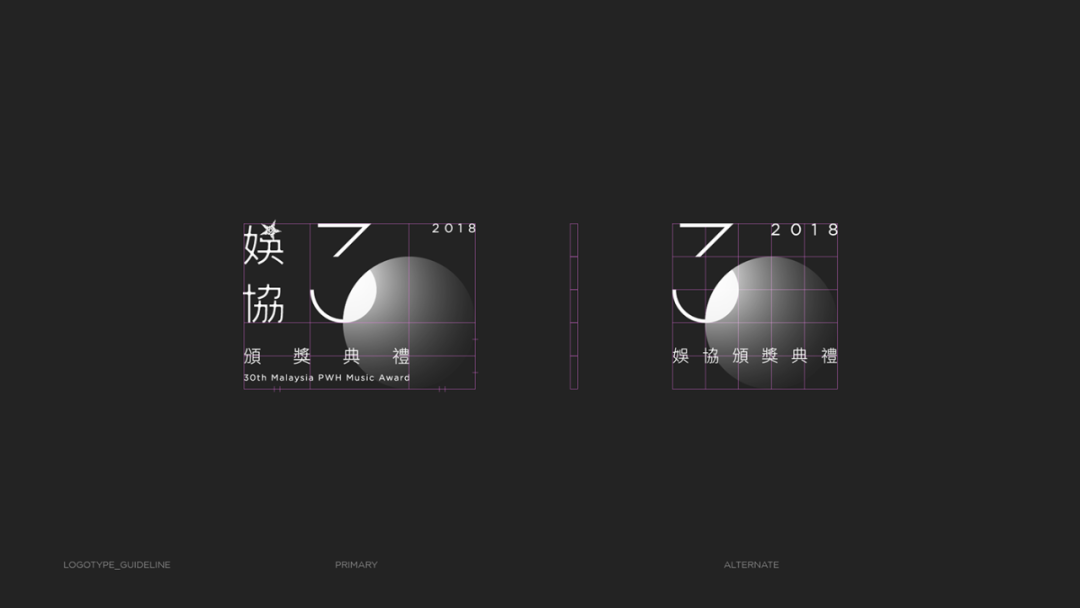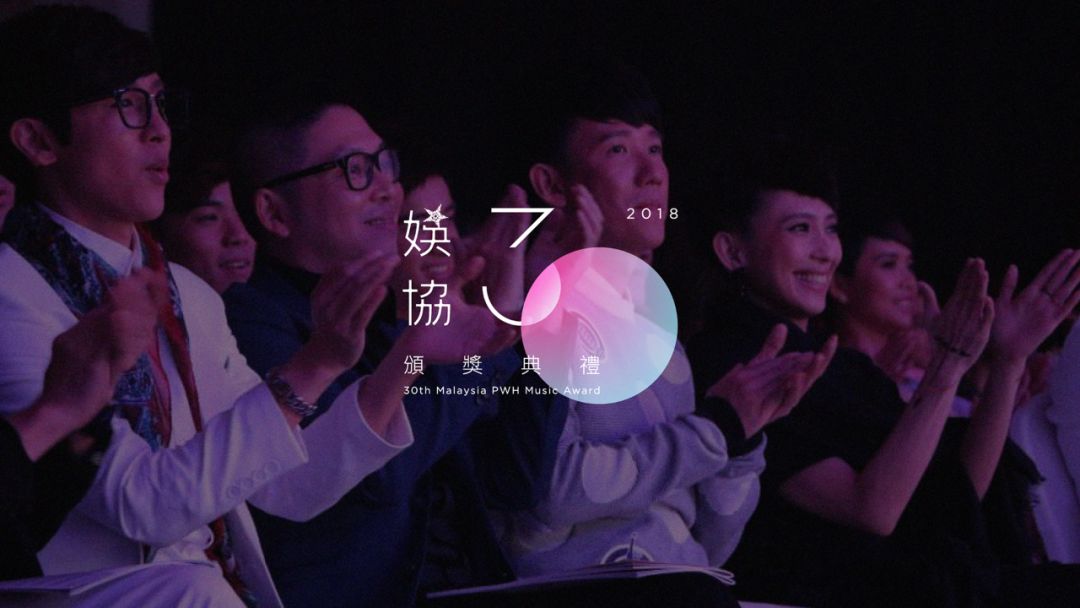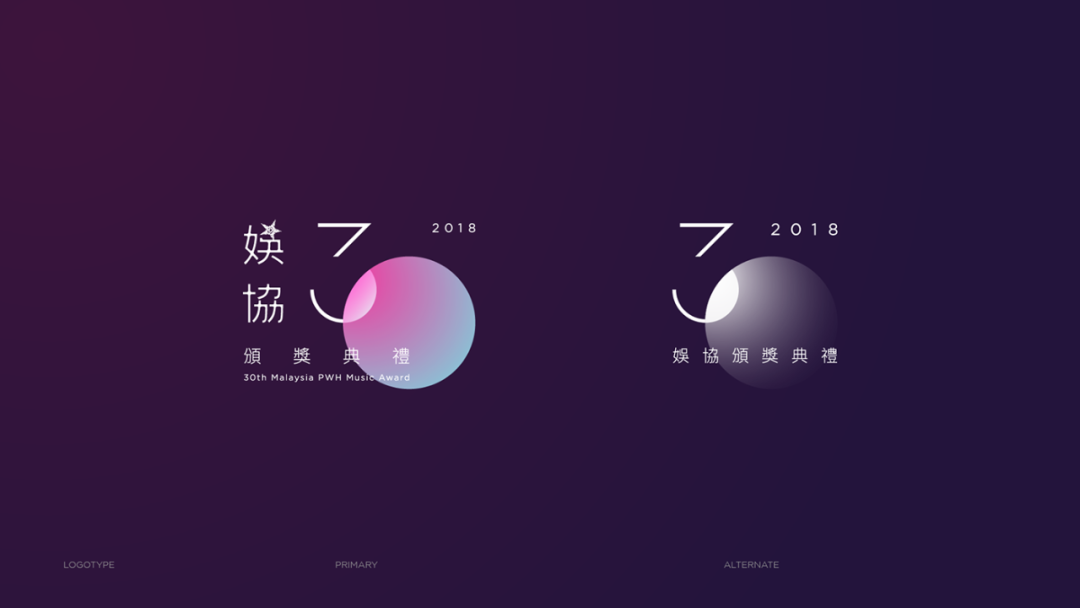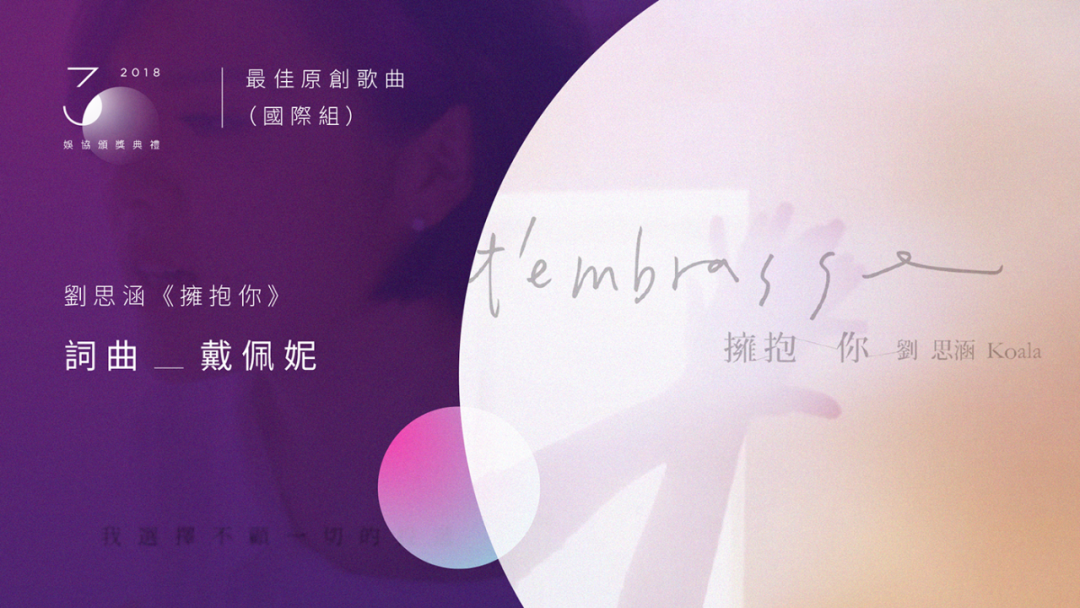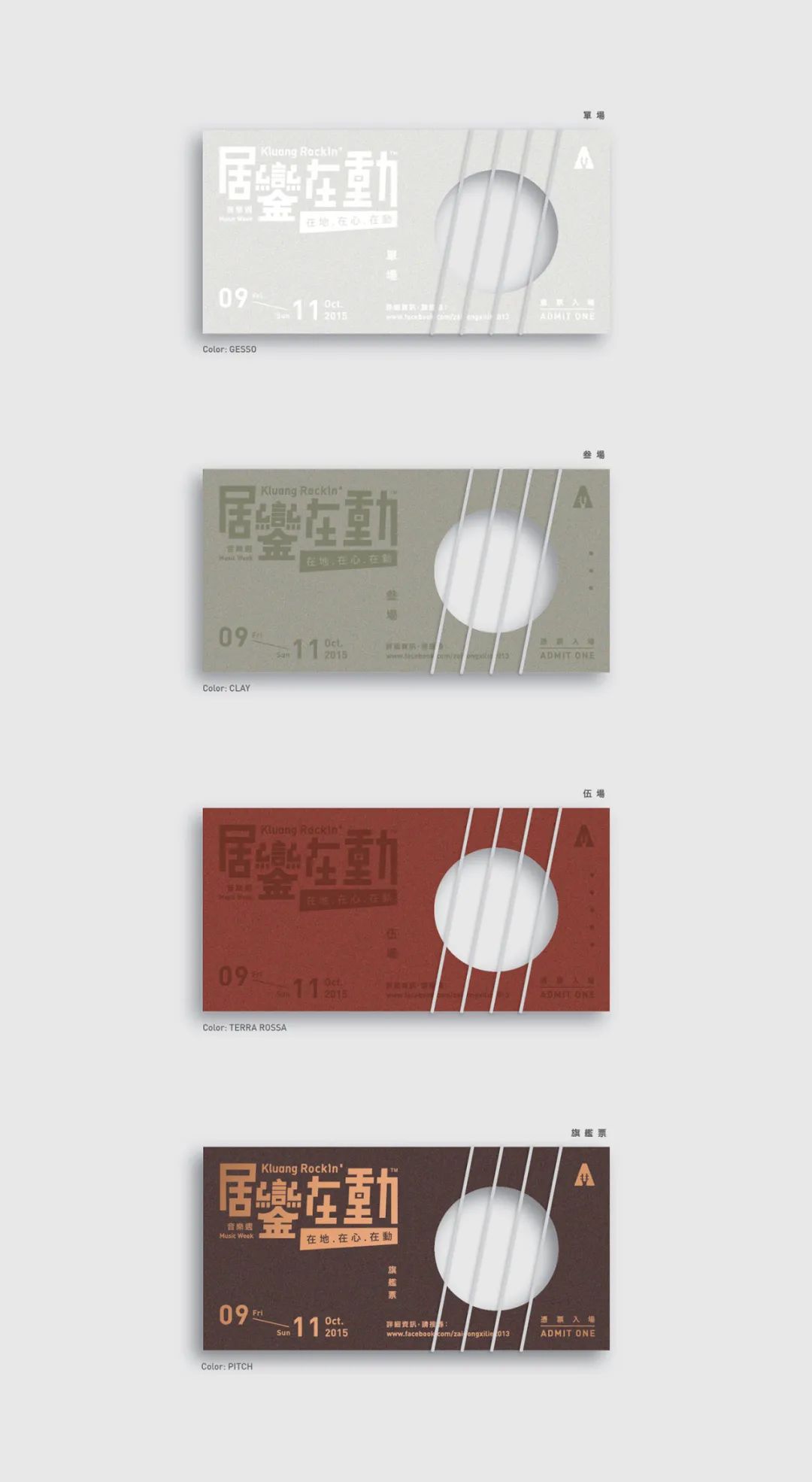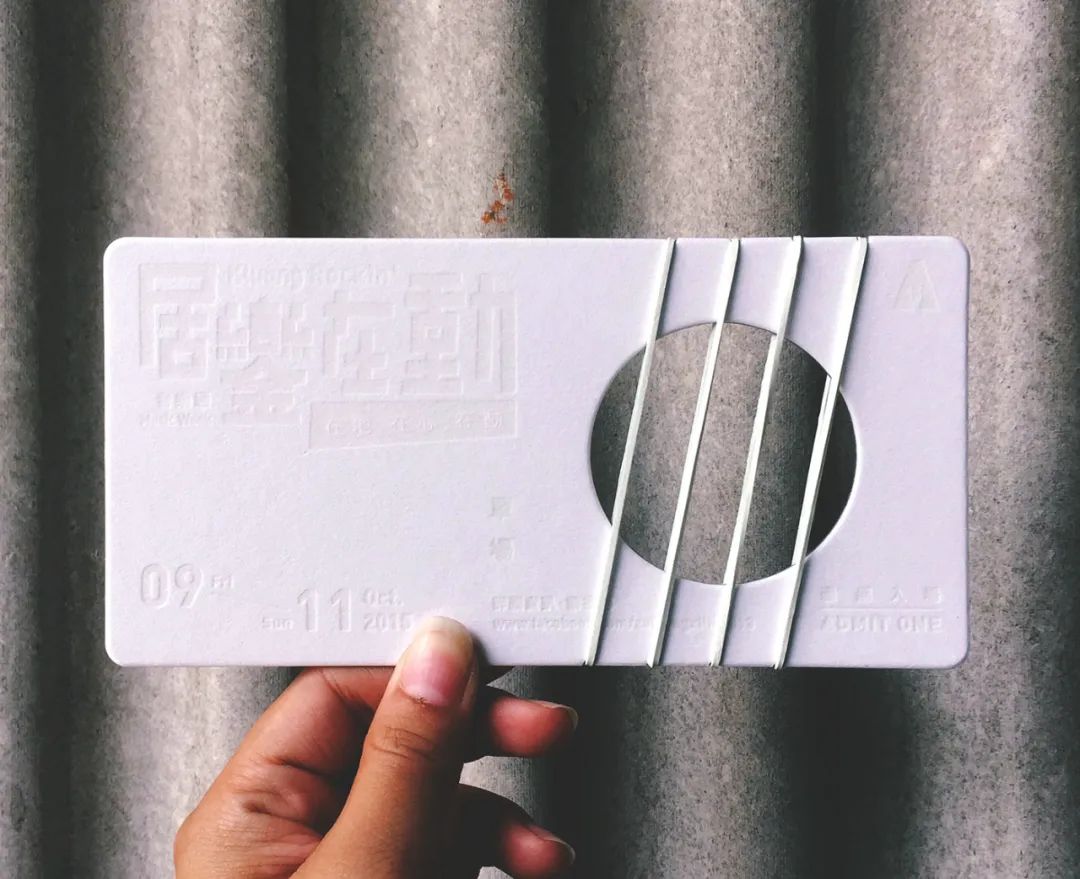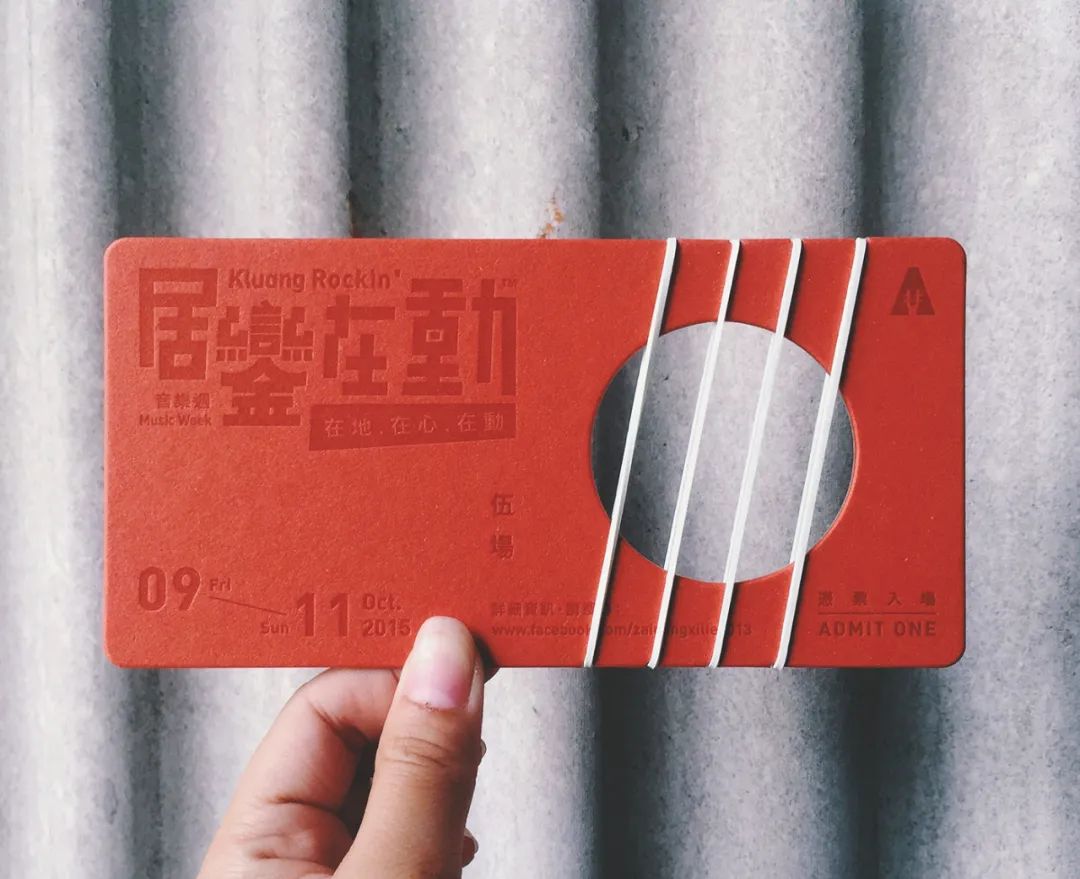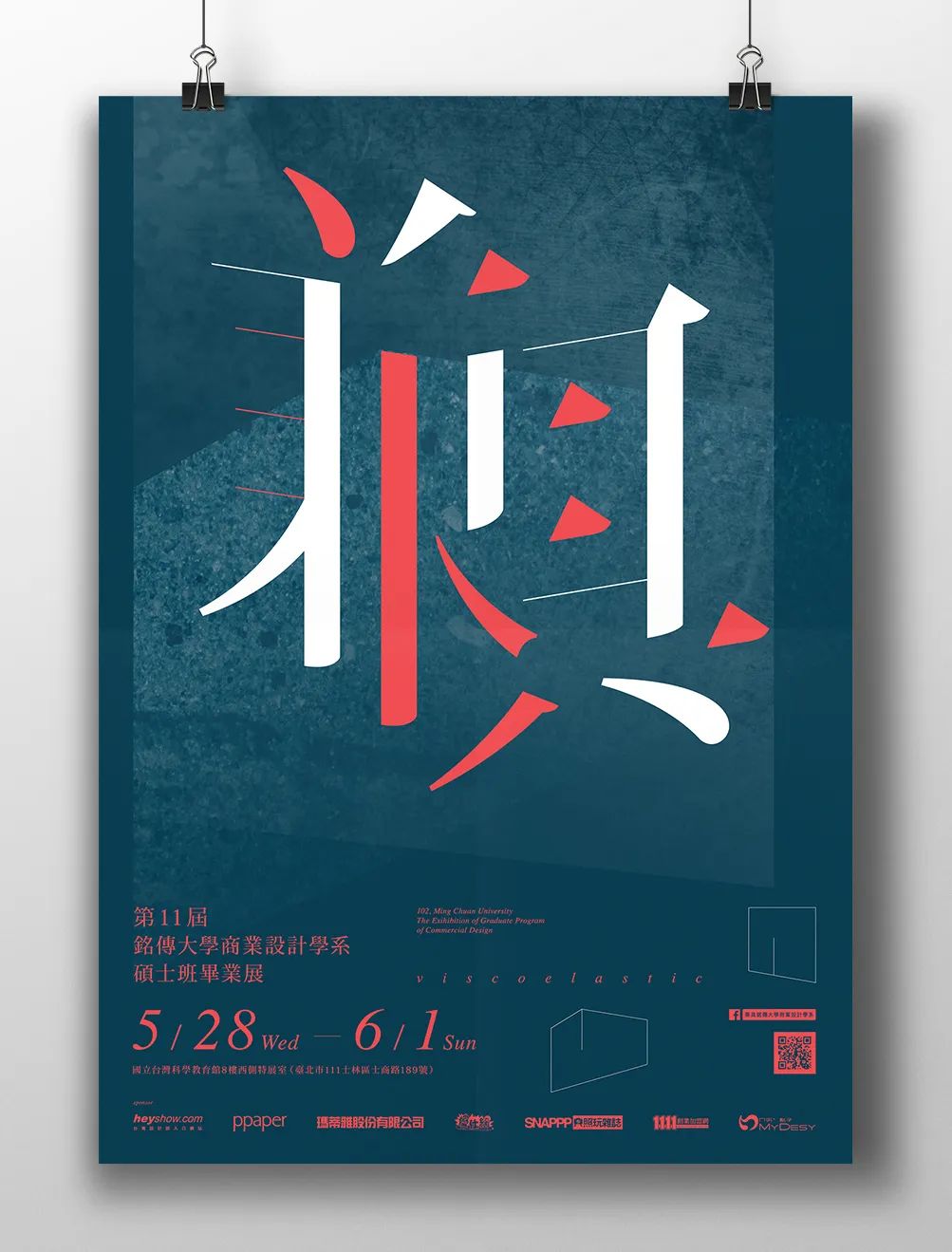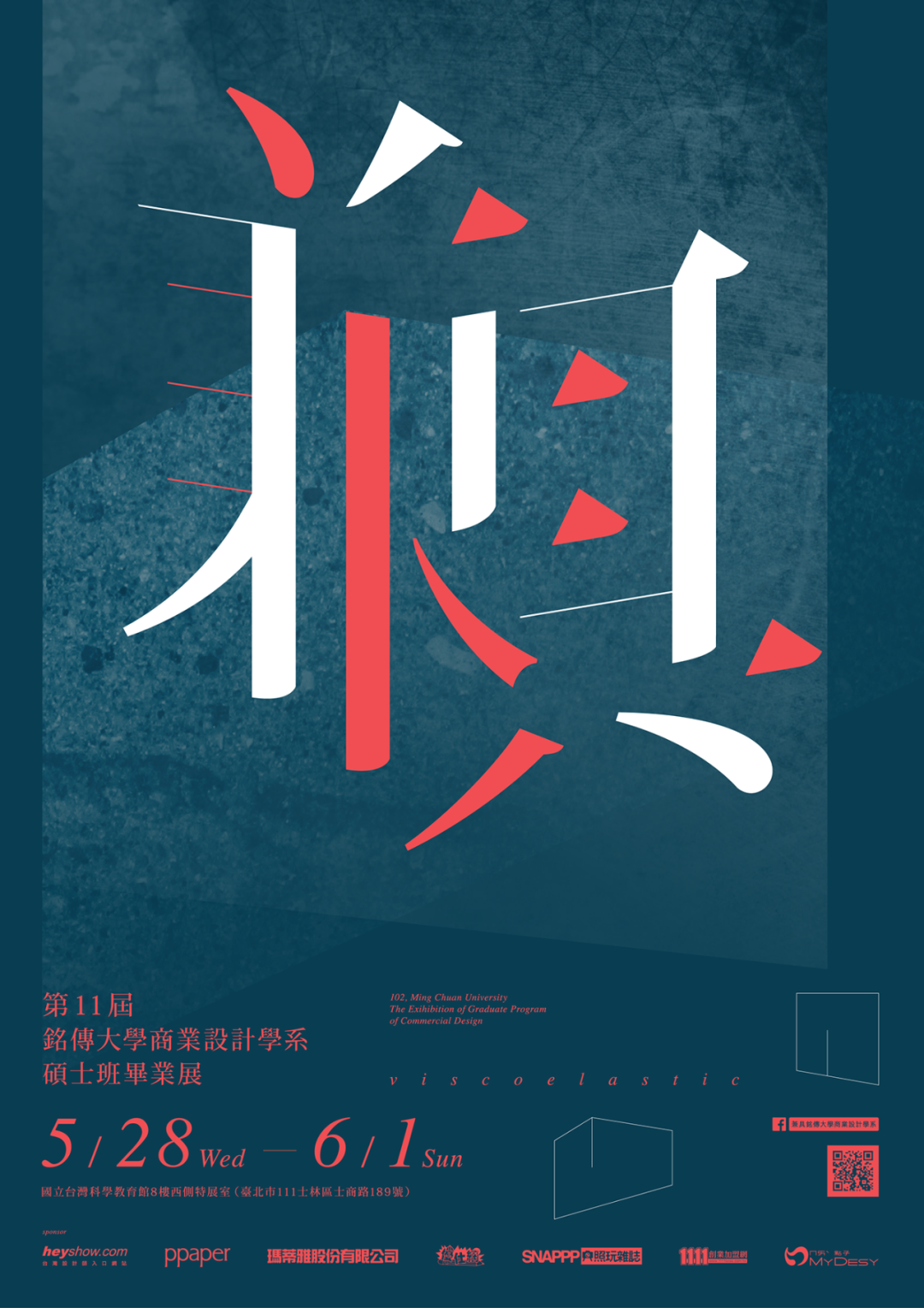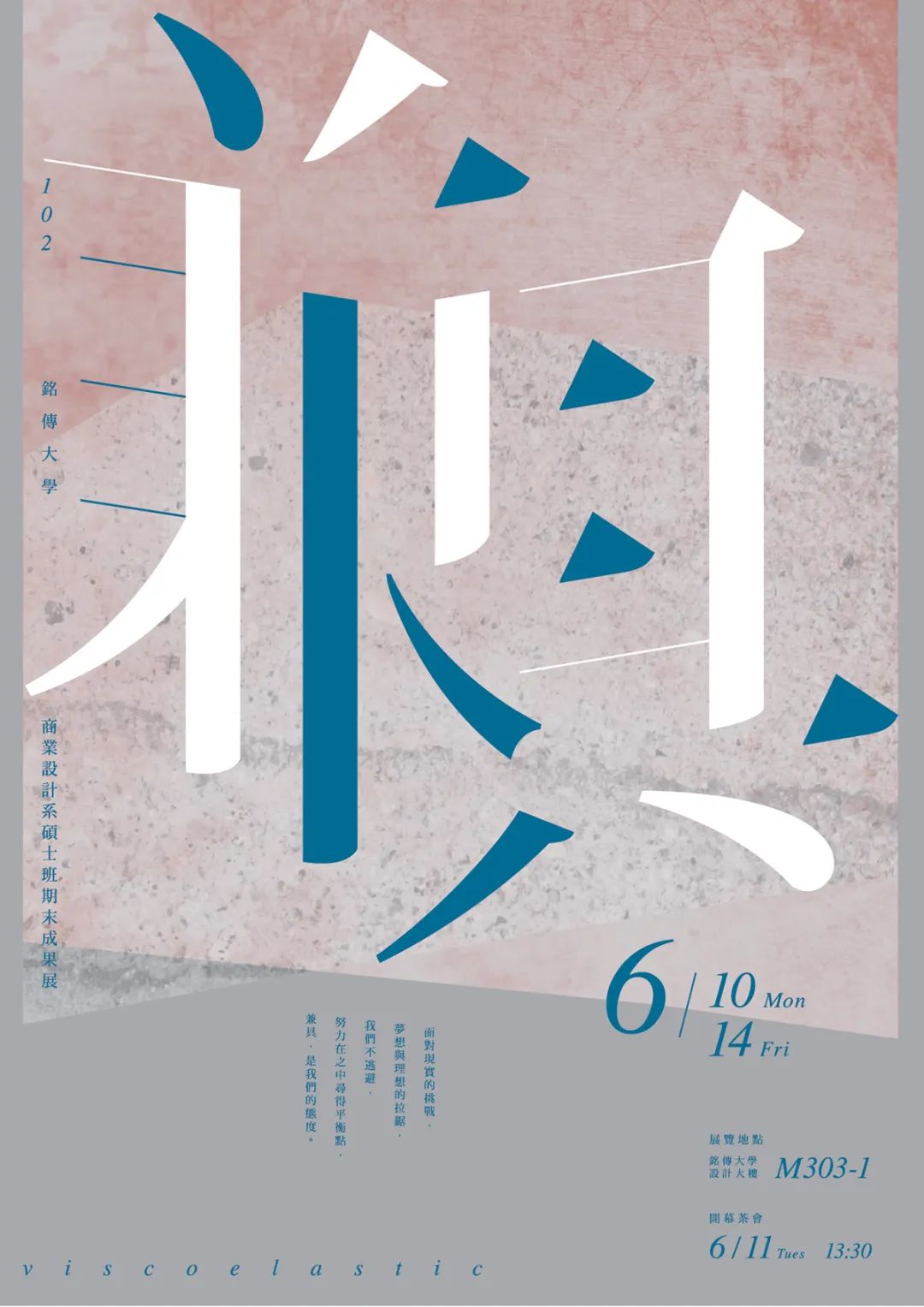
他擅长不同材质与手作设计字型
今天,和大家介绍和认识一下来自马来西亚设计师 KF Lim。
KF Lim 土生土长于马来西亚-沙巴州,2009年为了追求梦想,远赴台湾就读商业设计科系。2014年研究所毕业后,任职于台北一间知名的创意策略、品牌定位与视觉设计公司—JL Design。除了擅长于平面设计、字型设计以外,更喜爱尝试将不同材质媒材与手作技法应用于设计创作上。
介绍完他本人之后,来通过他的设计作品认识一下他。
01
娱协30颁奖典礼(视觉概念)
设计师 KF Lim 利用色彩与滤镜特效的手法表现光芒、光晕,希望以光去荣耀音乐工作者,不管是舞台上的聚光灯或是对作品的坚持而看过无数清晨的曙光,都是对他们在音乐路上付出与贡献给予肯定!
标准字设计
Logotype _ guideline
奖项/颁奖人 _ 字卡设计
Awards / presenter title card _ guideline
入围/获奖 _ 字卡设计( 奖项名称 最短 1 行 与 最长 2 行 )
Nominee / winner title card _ guideline
02
Clé de Peau Beauté肌肤之钥15週年品牌形象影片
该影片,藉由品牌VIP顾客和资深员工的访谈,象徵品牌的钥匙打开代表人生不同面向的「门」作为譬喻,和你、我相互陪伴的我「们」双关语意,和开啓女性内在光耀能量与信念的那把金色钥匙所相互交织出的三组动人故事。
《居銮在动》音乐节
设计理念-
《居銮在动》音乐节的主办单位与活动地点是一间提供乐器贩售、音乐教学的複合式艺文咖啡厅。店里主要贩售的乐器有ukelele,因此以ukelele的造型为设计概念,利用异材质(橡皮筋)去表现琴弦,增添互动性与趣味性。印刷技术部分找了马来西亚有名的凸版印刷工作室 The Alphabet Press (TAP) 合作,选择以强调质感与触感的凸版印刷技术,提升门票的精緻度与收藏价值。
handmade postcard-好马不吃回头草
W I S D O M Handmade Typography project
三组实验字体
最后,和大家看看他的几组字体海报设计。